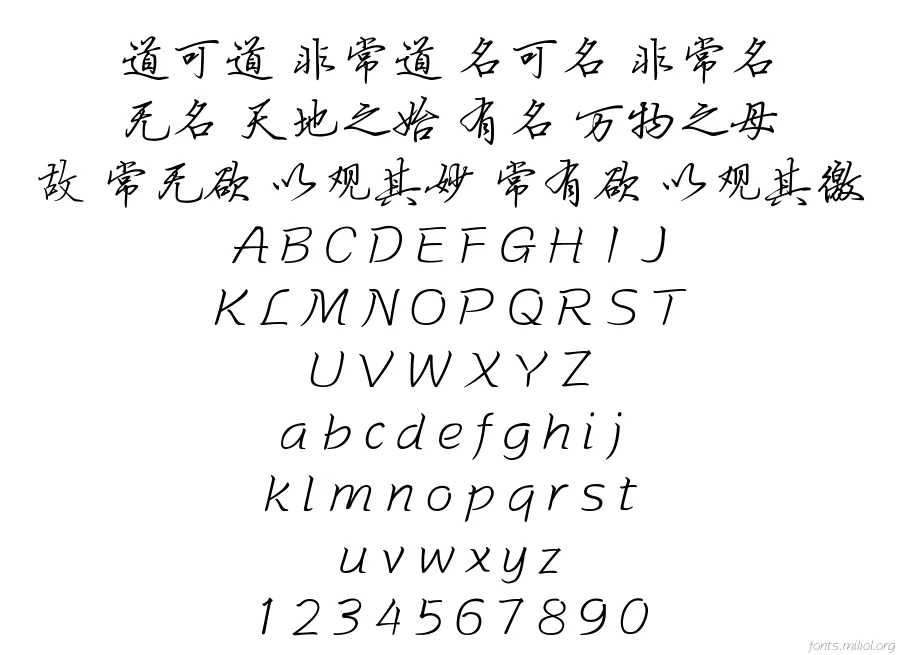
《方正硬笔行书_GBK:传统与数字的书法交融》
方正硬笔行书_GBK(FZYingBiXingShu-S16)是一款兼具实用性与艺术性的中文字体,以硬笔书法的行书风格为基础,融合了现代数字设计理念。其笔划流畅自然,结构疏密有致,既保留了传统行书的洒脱韵味,又通过标准化处理提升了屏幕显示的清晰度,适合日常办公、教育排版及创意设计等多种场景。
作为GBK编码字体,它完整支持简体中文、繁体中文及生僻字符,解决了多语言环境下的兼容性问题。字体设计中,横竖笔画的粗细对比明显,转折处带有硬笔特有的力度感,整体风格刚柔并济,既符合现代审美,又传递出浓厚的文化底蕴。
在数字化时代,方正硬笔行书_GBK为电子文档、广告印刷等领域注入了手写体的温度,成为连接传统书法与现代技术的重要载体。其命名中的"S16"代表标准字重,均衡易读,是追求效率与美感平衡用户的理想选择。